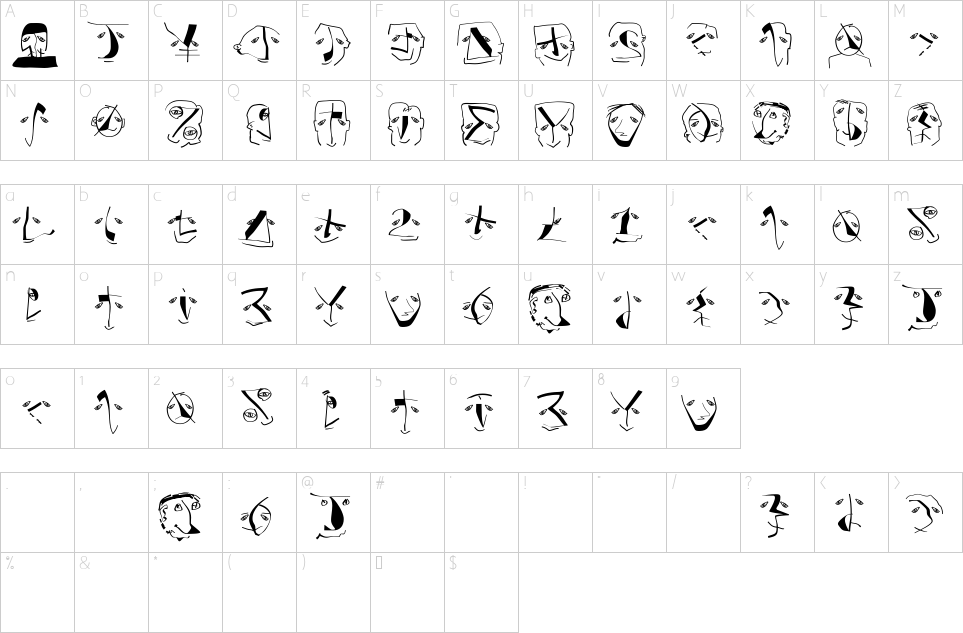
Descubra o vibrante universo da AnAlphaBetIsm Xtreme, uma fonte de graça para Windows e Mac, projetada pelo designer Manfred Klein. Esta fonte traz alegria à sua escrita com seus traços precisos e elegantes, adaptando-se perfeitamente para criar textos atraentes e agradáveis aos olhos. Com sua disponibilidade gratuita, você pode explorar os recursos que esta fonte tem a oferecer, desde o seu uso em projetos pessoais até o desenvolvimento de sites e apps. Com 2,539 downloads, você pode estar certo de que esta fonte é uma escolha inteligente para aqueles que valorizam o design gráfico de qualidade. Experimente a AnAlphaBetIsm Xtreme hoje e adicione um toque de sofisticação a suas criações.